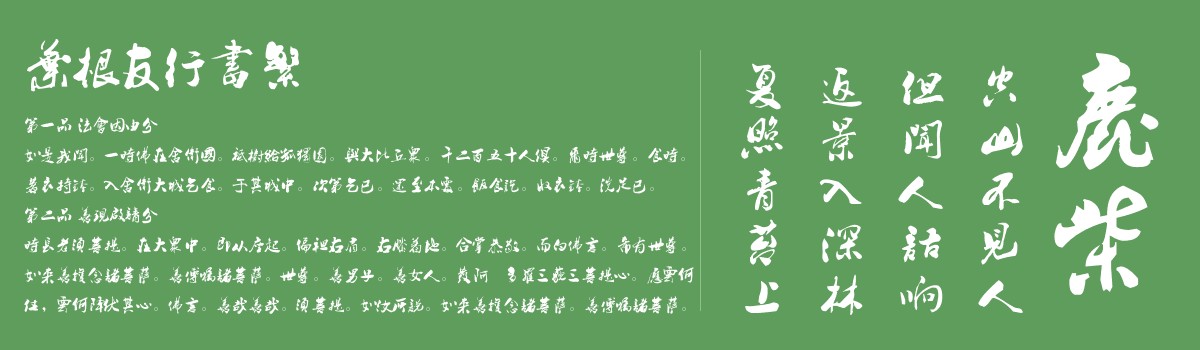
叶根友行书繁
创作年代:2007年
字体作者:叶根友
这是一款叶根友字体系列最受欢迎的字体之一,没有之二!叶根友毛笔行书简体是具有独特风格的字体,笔意取自米芾书法风格,大气而又自然流畅是这款字体的主要风格。广泛应用于社会各界的广告招牌、影视作品以及游戏应用等。
一款2007年创意的字体,笔画风格大气流畅,书写自然,是一种纯手写字体的经典之作,之前第一版显示叶根友毛笔行简体“明”字错误,在2011年时已经更正该错误,请各用户注意甄别,如善未替换的用户请重新下载该升级版叶根友毛笔行书字体,2012年升级完成2.0版本升级,调整了字数上下距离、大小等。
创作记事
2008年2月,初创该字体字稿
2008年11月,发行叶根友行书繁1.0版本
2012年3月,更正叶根友行书繁个别字显示位置调整问题
2014年10月,修正叶根友行书(繁)袋字的错误修正问题
2016年将计划补全该套字体其他未写的汉字,很多网友问这套叶根友行书繁体有没有简体?其实在2015年发布的叶根友畅行书就是这套叶根友行书繁字体的简体版本,只是时隔这么多年,书写的手法和创意理念发生了变化,使叶根友畅行书的风格跟这套字体有比较大的出入。